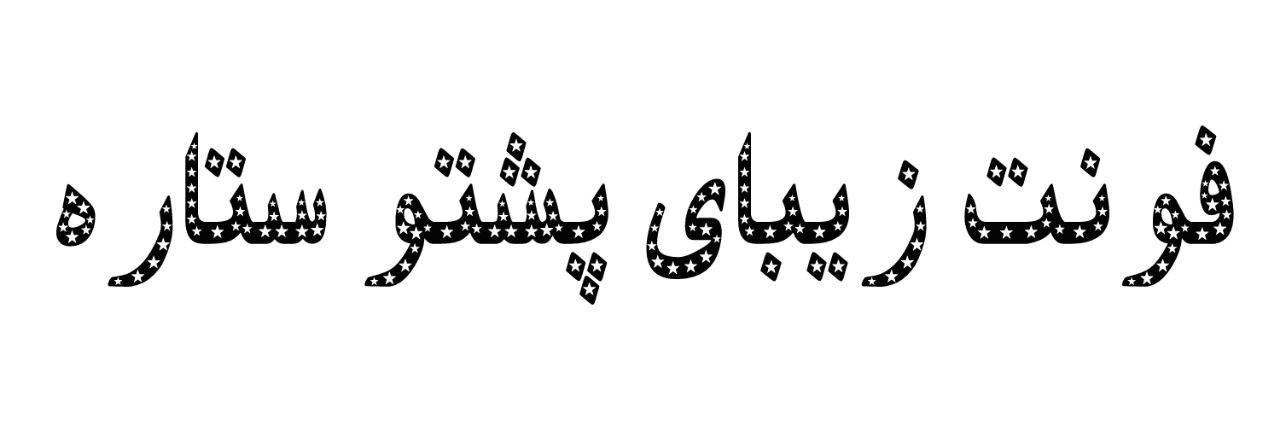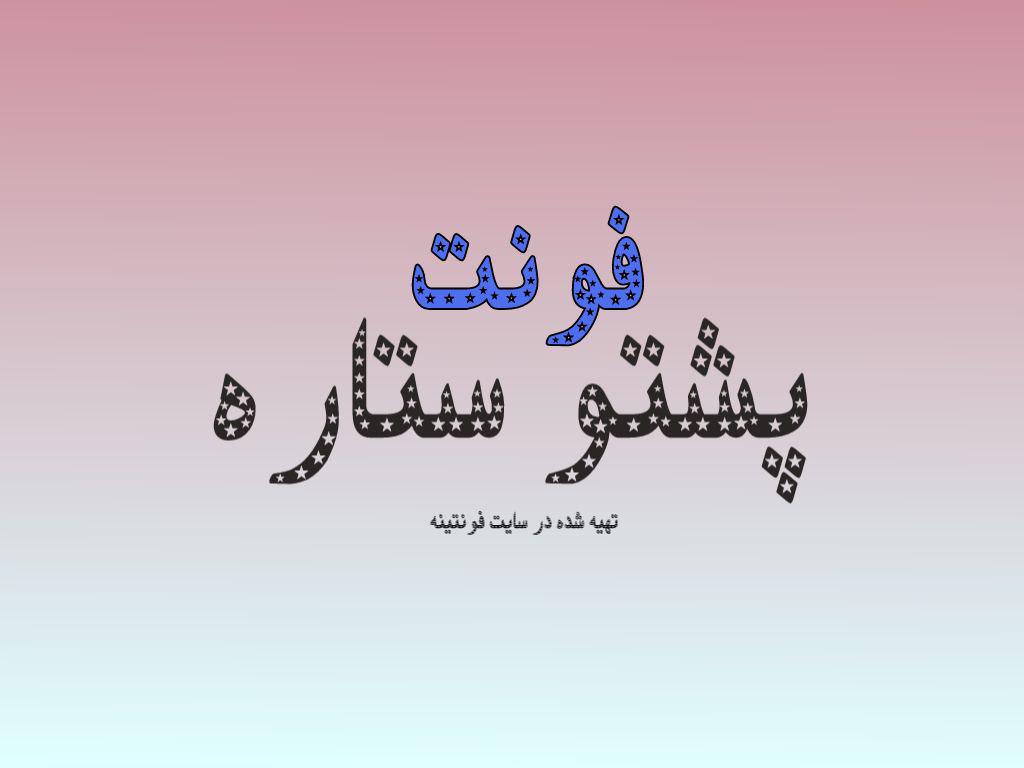
دانلود فونت پشتو ستاره در خدمت شما بزرگورارن هستیم با ارائه فونت زیبا و فارسی پشتو ستاره این فونت برای طراحی های لوگو و بنر و…. مورد استفاده قرار میگیرد.
ویژگی های فونت پشتو ستاره :
تصاویری زیبا از طراحی های خاص با فونت پشتو ستاره که برای نمایش و نمونه پیش فرضی از نمایش این فونت کاربردی طراحی شده است